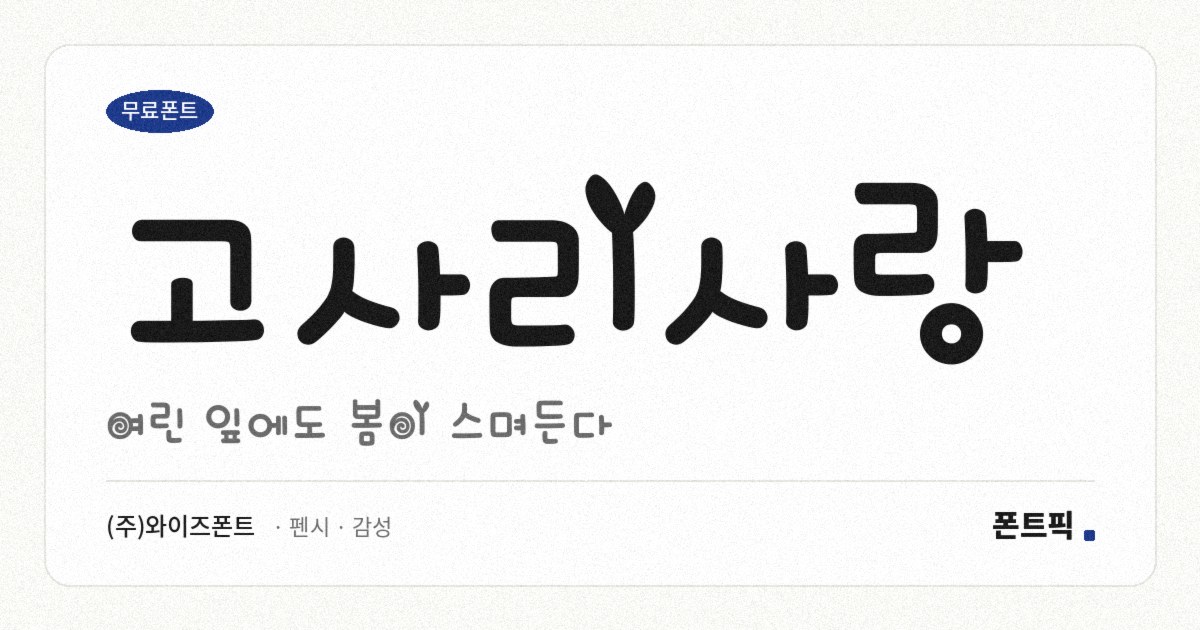
고사리사랑
TDTDFernLove
획 끝이 새순처럼 안쪽으로 동그랗게 말려 드는 손글씨 서체입니다. 이름의 고사리가 그 말린 형태를 가리킵니다. 나의 곁줄기 끝처럼 획이 마무리되는 자리마다 그 말림이 나타납니다.
파일에서 재어 보면 가로획과 세로획의 굵기가 거의 같아 획이 고르고, 받침이 붙을 때 글자가 0.29em 내려가는 탈네모틀입니다. 획이 통통한 편이라 작은 크기에서도 형태가 또렷하게 남습니다.
어린이 콘텐츠 제목이나 영상 자막 한 줄에 쓰기 좋습니다. 다만 말린 획이 서로 가까워 문장이 길어지면 답답해지니 두세 어절에서 끊는 편이 낫습니다. 현대 한글 11,172자를 모두 담았고 굵기는 하나입니다.